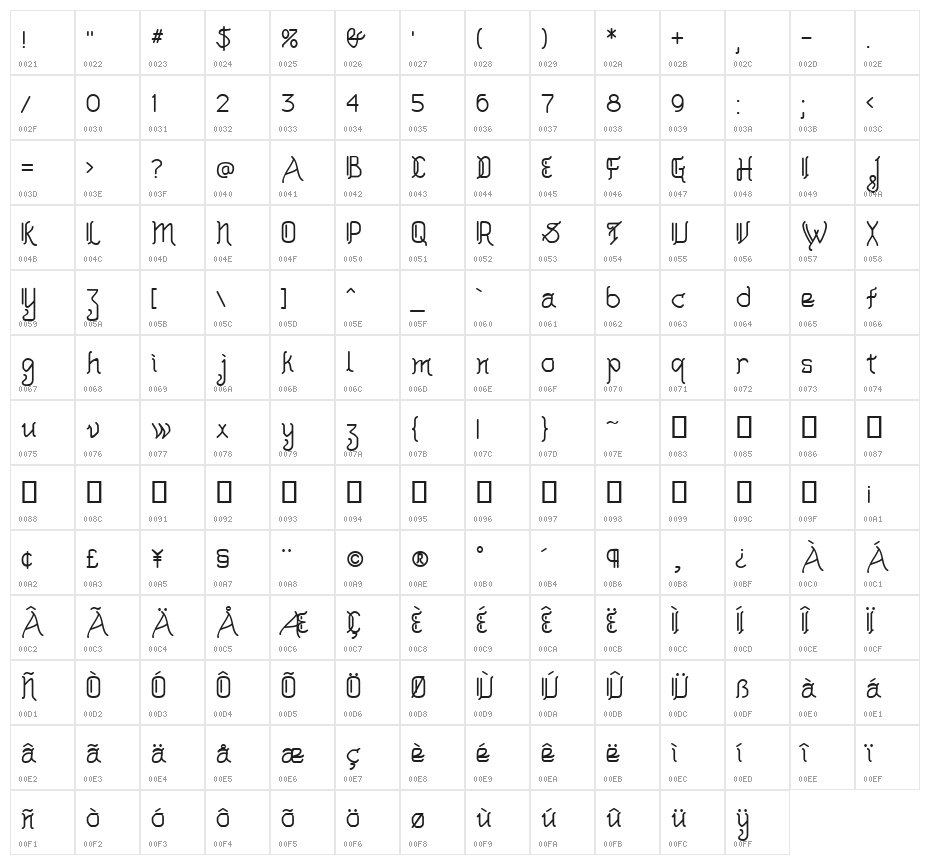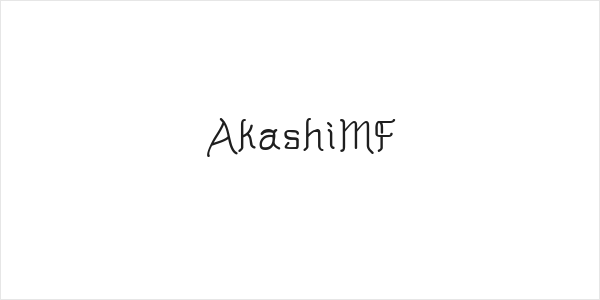
AkashiMF Font
| Stile generale | Modern, Vintage |
| Caso d'uso | Logos, Posters, Artistic Designs |
| Progetti proposti | Ideal for branding, logos, posters, and artistic designs that require a distinctive and stylish appearance. |